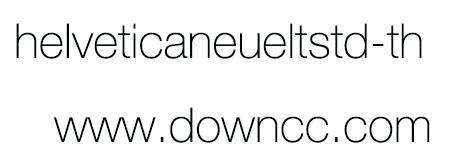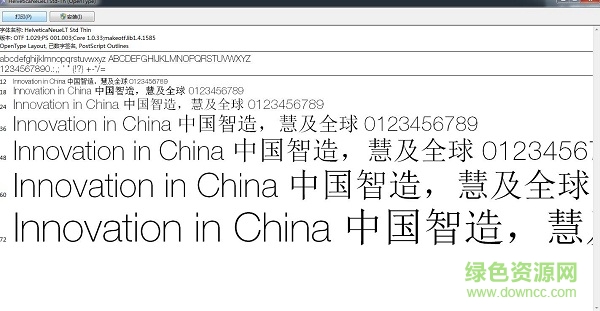
helveticaneueltstd-th字體是這套字體里面最細的一款,現代大氣,沒有任何手工的痕跡,十分地標準化,適合用在時尚品牌、電子屏幕等方面,歡迎免費下載!
【優(yōu)點】
Helvetica的出現就像一股清流,它去掉了多余設計,關注字體本身的結構,給設計界帶來更優(yōu)質的可選方案。
【缺點】
Helvetica的設計理念是一致、去個性,字母的整體造型都偏圓,因此缺乏閱讀韻律